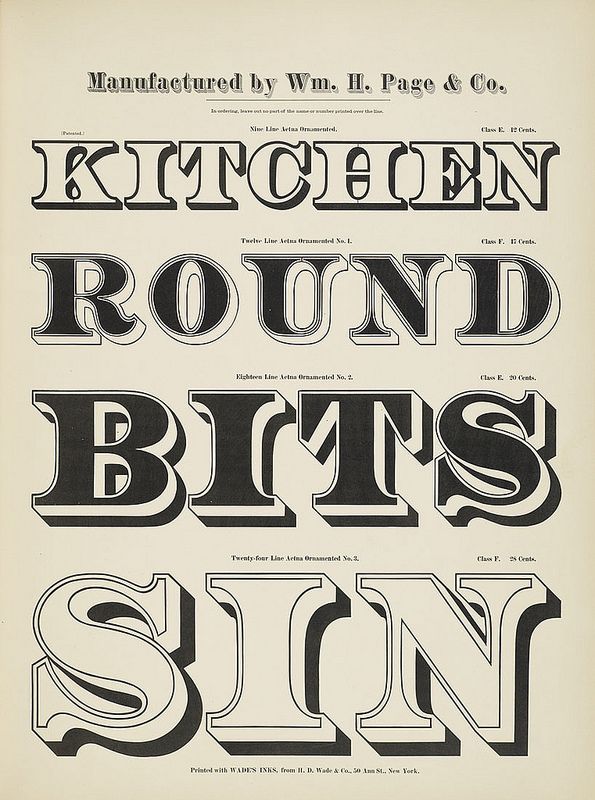
74. Шрифтовые формы XIX века
До
конца XVIII века различия между книжными,
рекламными и газетными шрифтами не
существовало, употреблялся один и тот
же шрифт, но разного размера. С активным
развитием промышленности и торговли в
XIX веке начали возникать новые стили
шрифтов для газетных объявлений, рекламы
и других акцидентных (т.е. выполняемых
по случайным, разовым заказам) работ.
Эти шрифты отличались от книжных особым,
бросающимся в глаза рисунком. Эксперименты
в области шрифтовой формы привели к
возникновению новых видов шрифта.
К
таким акцидентным
шрифтам принадлежит
появившийся в начале XIX в. египетский
или
брусковый
шрифт.
Отличительным
признаком этого шрифта является
одинаковая толщина всех линий и засечек
букв. При этом пропорции и расположение
засечек такие же, как у антиквы. Существуют
разновидности египетского шрифта с
большим или меньшим различием в
насыщенности основного и дополнительного
штриха. Известнейшие из типографских
египетских шрифтов — Мемфис и Бетон
работы немецких шрифтовиков Рудольфа
Вольфа и Гейнриха Иоста.
Существует
два подвида египетского шрифта.
Первый
из них — это итальянский
шрифт,
весьма популярный в XIX в. Это узкий шрифт,
по строению напоминающий рустику.
Горизонтальные штрихи в несколько
раз толще вертикальных.
Второй
подвид египетского шрифта — это
кларендон.
Его признак — слегка округленные засечки
и больший контраст между толщиной
основного и дополнительного штриха.
В
1816 году появляется шрифт, на фоне
многовекового господства антиквы
выглядевший странно и даже смешно,
за что и получил свое название — гротеск
(от
фр. смешной). Это шрифт с минимальным
контрастом между основным и дополнительным
штрихами и полным отсутствием засечек.
Гротески,
как и египетские шрифты, создавались в
качестве акцидентных и на большее не
претендовали. Однако в 1896 году берлинская
словолитня «Бертольд» выпустила
серию шрифтов, которые, несмотря на свое
название «Акцидент-гротеск», оказались
пригодными для набора текстов.
Акцидент-гротеску предстояло стать
прототипом новой шрифтовой эстетики.
Он появился незадолго до того, как
«новые типографы» назвали гротеск
«объективным и наднациональном шрифтом
современности». И действительно, именно
гротески обусловили облик типографики
XX в.
Кроме
названых шрифтов в XIX в. на фоне общего
упадка типографических традиций
появляется огромное количество
декоративных шрифтов, как правило —
искаженных, противоестественных форм.
Конструктивная неясность и декоративная
перегруженность таких шрифтов формировала
тенденцию к упадку художественного
шрифта во второй половине XIX в., периоде,
получившем название периода
типографической эклектики.
Примерно в 1808
году Пеллегрино
Турри (Pellegrino Turri), также известный как
изобретатель копировальной
бумаги, создаёт собственную печатную
машину. Подробности о его изобретении
сегодня неизвестны, однако до нашего
времени сохранились тексты, напечатанные
на этом устройстве.[3]
Эпоха
ренессанса не расширяла никогда
первоначальной формы шрифта. Дидо,
наоборот, выдвинул положение о серии
шрифтов — узких, широких, жирных, тонких
и т. д.
В
XIX в. было создано огромное количество
всевозможных шрифтов самых разнообразных
рисунков. В Англии в начале столетия
появляется характерная разновидность
шрифта с чрезвычайно тонкими дополнительными
штрихами и одновременно чрезвычайно
жирными основными.
Это
так называемый жирный гротеск Торна
(1803 г.), за которым последовал в 1824 г. еще
более жирный шрифт (рис. 318). Не следует
путать этот шрифт с гротесковыми шрифтами
в современном смысле этого слова. В
настоящее время мы называем гротесками
шрифты типа древнего (рубленый,
рояль-гротеск и т. д.).
Появление |
Застрельщиком
была Англия как страна с наиболее
развитой промышленностью. Континентальная
Европа покупала английские машины и
копировала английские шрифты. Франция,
Германия, Голландия, Испания выпустили
ряд шрифтов. Появились жирные шрифты
самых различных рисунков, соответствующих
рисункам светлых шрифтов.
Появление
гротесковых шрифтов (в современном
значении этого слова) относится к первой
половине XIX в.
Шрифты
в стиле модерн и экспериментальные
шрифты
своими характерными начертаниями ярко
отражали стиль того времени.
Лучшие
шрифты нашего времени созданы выдающимися
художниками шрифта.
Их благородные формы возникли в итоге
изучения красоты и практичности всех
прежних шрифтов. Создать шрифт могут
лишь немногие. Шрифтовое оформление
требует больших практических знаний.
Типографические шрифты часто
называют по имени создателей, но иногда
им дают звучные собственные имена.
В
XIX в. было создано огромное количество
всевозможных шрифтов самых разнообразных
рисунков. В Англии в начале столетия
появляется характерная разновидность
шрифта с чрезвычайно тонкими дополнительными
штрихами и одновременно чрезвычайно
жирными основными.
Появление
гротесковых шрифтов (в современном
значении этого слова) относится к первой
половине XIX в.
В
начале XIX в. появляется так называемый
«египетский» шрифте утолщенными
отсечками, перпендикулярными к основным
жирным штрихам.
Историческая
классификация наборного шрифта
Антиква |
|||
XV–XVI |
Гуманистическая (антиква |
Aa (Garamond) |
Шрифты |
XVII–XVIII |
Переходная антиква |
Aa (Caslon) |
Шрифты |
XVIII–XIX |
Классицистическая |
Aa (Bodoni) |
Шрифты |
Брусковые |
|||
Начало |
Египетские |
Aa (Luxor) |
Насыщенные |
Начало |
Итальянские |
Aa (Italiansky) |
Шрифты |
Начало |
Кларендон |
Aa (ScoolBook) |
Разновидность |
Гротески |
|||
Вторая |
Старые |
Aa (Gazeta) |
Ранняя |
20-е |
Геометрические |
Aa (Futura) |
Шрифты, |
50-е |
Новые |
Aa (Pragmatica) |
Моноширинные, |
50-е |
Гуманистические |
Aa (Optima) |
Шрифты |
Конец |
Динамические |
Aa (FreeSet) |
Разноширинные |
ренессансная антиква — Оди. О дизайне
27 Апр 2022
8771
0
Переходим к классификации текстовых шрифтов.
Паратайп
Паратайп — первая шрифтовая студия в России. Мы делаем новые шрифты, поддерживаем магазин paratype.ru, рассказываем о шрифте и типографике.
Если ориентироваться на форму, то в зависимости от степени контраста и наличия засечек они делятся на четыре основные группы: антиква, гротеск, брусковый шрифт и ленточная антиква/контрастный гротеск.
Антиква (Serif)
Из современных видов текстовых шрифтов первыми появились антиквы — шрифты с засечками и заметным контрастом между горизонтальными и вертикальными штрихами. До начала XIX века это был практически единственный тип шрифтов в Европе (если не считать готических шрифтов в Западной Европе и полууставных в Восточной).
Антиква старого стиля (Old style serif)
Отличается самой геометрически «неправильной» формой среди текстовых шрифтов. Это объясняется относительной близостью шрифтов этого типа к рукописному прототипу.
Как правило, для старостильной антиквы характерен умеренный контраст (1:2–1:3), открытость форм, наклонные оси овалов, часто — несимметричные засечки.
Антикву старого стиля можно назвать ещё динамической антиквой, т.к. формы, унаследованные от гуманистической каллиграфии, как бы помогают глазу двигаться по строке.
Старостильные антиквы с ярко выраженным характером больше всего подходят для набора текстов своего времени (от Ренессанса до барокко). Антиквы старого стиля с менее выраженным характером — самый подходящий шрифт для художественной литературы. Из-за небольшого контраста и открытости форм она легко читается в очень длинных текстах.
Антиквы старого стиля делятся на ренессансные (XV–XVI вв.) и барочные (XVII–начало XVIII в.). У каждой из этих групп по две подгруппы. Ренессансные антиквы бывают венецианские и итало-французские, а среди барочных антикв выделяют голландские и английские.
Венецианская антиква (Venetian old style serif)
Шрифт Николая Иенсона из книги Vitae Imperatorum, 1471 г.
Время появления: конец XV века
В двух словах: Самый ранний тип антиквы и самый близкий к каллиграфии ширококонечным пером. Несимметричные формы овалов и засечек, очень разноширинные пропорции, небольшой контраст, мелкие строчные буквы и длинные выносные элементы.
История и теория: Венецианская антиква — собирательное название ранних антиквенных шрифтов, в основном применявшихся венецианскими типографами конца XV века. Форма знаков основана на дуктальном принципе. Шрифты характеризуются умеренным контрастом, мощными короткими засечками, хорошо выраженным наклоном осей овалов. Пропорции знаков довольно широкие, знаки разноширинные. Круглые элементы имеют каллиграфические изломы, каплевидные элементы угловатые. Засечки чуть прогнутые. Соотношение величины строчных и прописных близко к золотому сечению. В оригинальных венецианских шрифтах этого периода не было курсивов, изобретенных позже. Характерная особенность – наклонная перекладина у строчной «е». Наиболее характерные шрифты этого типа – шрифты венецианского типографа и словолитчика Николая Йенсона (Nicholas Jenson, работал в 1470–80 гг.).
Примеры цифровых шрифтов
LazurskiLeksaLadogaVenetian 301
Итало-французская антиква (Garalde)
Фрагмент печатной книги 1597 г.
Время появления: конец XV века
В двух словах: Ранний тип антиквы, один из самых красивых в истории наборного шрифта. Встречается в лучших образцах ренессансной печатной книги. По форме мягче венецианской антиквы, детали более округлые. Несимметричные формы овалов, разноширинные пропорции, небольшой контраст, мелкие строчные буквы и длинные выносные элементы.
История и теория: Гаральды или итало-французская антиква старого стиля — собирательное название группы ранних антиквенных шрифтов, основанных на шрифтах венецианского типографа и издателя Альда Мануция (Aldus Manutius, 1447–1515) работы болонского гравера Франческо Гриффо (Francesco Griffo, ок. 1450–1518) и парижского словолитчика Клода Гарамона (Claude Garamond или Garamont, ок. 1490–1561). Название «Гаральды» означает шрифты, близкие к ГАРамону и АЛЬДу.
Aldus ManutiusClaude Garamond
Развитие венецианской антиквы в конце XV–XVI в.в. Название придумано французским исследователем типографики Максимилианом Воксом (Maximilien Vox) в 1954 г. Форма знаков похожа на структуру предшественников и еще основана на дуктальном принципе, но заметно меняется под воздействием типографской практики и теорий построения шрифта Луки Пачоли (Luca Paccioli, ок. 1445–1514) и Жоффруа Тори (Geoffroy Tory, 1480–1533). Шрифты характеризуются небольшим контрастом, пропорциями золотого сечения, разноширинностью знаков, плавным присоединением засечек, наклонными осями овалов. Засечки становятся более длинными и острыми, верхние выносные элементы обычно заметно выше прописных. Впервые у Альда применяется строчной курсив с небольшим наклоном как альтернативный текстовой шрифт, но затем курсив рассматривается как дополнительное начертание к прямому, он согласовывается по размеру, цвету и форме, в нем появляются наклонные прописные. В курсиве наклон у прописных меньше, чем у строчных. Строчные курсивные знаки имеют разный наклон.
Примеры цифровых шрифтов
Aldine 401Iowan OldstyleRevival 565
Зачем в 2020-х годах может понадобиться ренессансная антиква?
Хотя этому типу шрифтов пятьсот с лишним лет, он прекрасно работает в тексте. Правда, не в любом: в качестве основного шрифта, например, на новостном сайте ренессансная антиква будет выглядеть странно. А вот в издании (в том числе электронном) на историческую тему в качестве заголовочного шрифта, в красивой книге с большими полями (особенно в волшебных сказках) для основного текста, или для создания нужной атмосферы — вполне! Особенно сильное впечатление производит ренессансная антиква, если набрать пару слов прописными с очень сильной разрядкой.
В следующей части мы расскажем о барочной антикве.
Первая часть.
Шрифты 1800-х годов: 35 лучших шрифтов 19-го века
Для графического дизайнера шрифты являются неотъемлемой частью вашего набора инструментов. Они делают или разрушают ваши проекты.
Шрифты 1800-х годов особенно привлекательны. Эпоха пережила революцию в шрифтах и типографике, и ее влияние все еще присутствует в современном графическом дизайне. Многие шрифты 19-го века причудливы и уникальны, с большим характером. Если вы хотите придать своему дизайну ощущение старины, это идеальный выбор.
Здесь вы найдете коллекцию лучших современных шрифтов, которые были разработаны, чтобы воспроизвести стиль 19-го века. От сложных рукописных шрифтов до классических шрифтов с засечками — здесь каждый найдет что-то для себя.
НЕОГРАНИЧЕННАЯ ЗАГРУЗКА: более 50 миллионов дополнений и ресурсов дизайна
Лучшие шрифты 1800-х годов Шрифты 19 века! Они выведут ваш винтажный дизайн на новый уровень.
Если вы любите шрифты, вам определенно стоит попробовать Envato Elements. Подписавшись на Elements, вы получите 90 009 неограниченных загрузок более 45 000 шрифтов , а также миллионов других ресурсов , таких как темы WordPress, стоковые фотографии, графика, звуковые эффекты и многое другое. Это лучшая ценность, которую вы можете найти в индустрии дизайна.
Euphoria
Euphoria — отличное семейство шрифтов 1800-х годов. Всего имеется 11 шрифтов, в том числе:
- Euphoria Victorian
- Euphoria Victorian Shadow
- Euphoria Victorian Gradient
- Euphoria Tuscan
- Euphoria Tuscan Gradient
- Euphoria Tuscan Outline
- Euphoria Serif
- Euphoria
- Euphoria Expand Bold
- Euphoria Sans
03 Serif10 Shadow
In Кроме того, пакет также поставляется с некоторыми дополнительными глифами для стилизации вашего текста. Чтобы использовать глифы, вам понадобится программа (например, Photoshop или Illustrator), поддерживающая функции OpenType.
Euphoria действительно больше, чем просто шрифт. Это набор красивых винтажных шрифтов, которые дают вам множество вариантов, когда вы хотите почувствовать аутентичность 1800-х годов.
Bahud Aroyek Декоративный шрифт 1800-х годов
Bahud Aroyek — это шрифт для дисплеев, созданный с искусным викторианским шрифтом. Он элегантный и идеально подходит для широкого спектра проектов, таких как брендинг, упаковка продуктов, одежда, товары и печатные материалы, такие как приглашения. Вам понравятся альтернативные стили и лигатуры, которые позволяют создавать текст, который выглядит так, как будто он был создан на заказ. Версия веб-шрифта также включена.
Chesterfield
Chesterfield — потрясающий шрифт 19 века, вдохновленный карнавальными, цирковыми и татуировками 1800-х годов. Благодаря декоративному стилю Chesterfield лучше всего смотрится в крупном тексте. Включены три варианта: обычный, обычный градиент и экструдированный. Пакет также включает 30 винтажных векторных форм, которые идеально подходят для создания значков и вывесок.
White Castle
White Castle — это викторианский шрифт, который прекрасно подходит для винтажных дизайнов. Это шрифт с заглавными буквами, в котором строчные буквы являются альтернативными версиями стилей в верхнем регистре. Также доступна версия веб-шрифта. Вам понравится использовать White Castle для брендинга, вывесок, значков и других винтажных дизайнов.
Taberna
Taberna — это огромная система шрифтов, включающая более 20 шрифтов 1800-х годов. Вы получите разновидности с засечками и без засечек с многоуровневыми версиями, которые можно накладывать друг на друга, а также монолинерный рукописный шрифт 19-го века. С Taberna в вашем арсенале у вас всегда будет доступ к множеству вариантов. Вам понравится использовать его для плакатов, заголовков, рекламы, этикеток продуктов, одежды и многого другого.
Liquidior
Liquidior — чистый шрифт с винтажным шармом. Он был вдохновлен древнегреческой типографикой, и вы обязательно найдете множество способов использовать его в своей работе. В пакет входят цифры, знаки препинания, лигатуры, многоязычные символы, а также некоторые значки и иллюстрации, которые можно использовать с текстом.
Wakers Amor
Wakers Amor — это шрифт blackletter с характером и стилем 1800-х годов. Он был создан с использованием викторианской типографики ручной работы и является отличным выбором для вывесок, брендинга, плакатов и других дизайнов с крупным текстом. Вы получите лигатуры, стилистические варианты, многоязычные символы и веб-шрифт.
Reborn
Reborn — многоуровневая система, включающая четыре шрифта: базовый, встроенный, теневой и орнаментальный. Вы можете использовать любой из шрифтов по отдельности или сложить их так, как вам хочется. Он поставляется с цифрами, пунктуацией и многоязычными символами. Вам понравится использовать Reborn для плакатов, листовок, упаковки продуктов, этикеток продуктов, брендинга, футболок, товаров и многого другого.
Гнилой банкет
Гнилой банкет может показаться странным названием, но оно станет выдающимся дополнением к вашей коллекции. Дизайнер был вдохновлен викторианской типографикой 19 века. Это декоративно, но все же легко читается. Пакет поставляется с огромной коллекцией из 370+ глифов для использования вместе с вашим текстом.
The Bhorthead
The Bhorthead — красивый винтажный шрифт для штампов, который идеально подходит для этикеток продуктов, упаковки продуктов, футболок, одежды, товаров и брендинга. Есть две версии: чистая и шероховатая (текстурированная), что обеспечивает дополнительную универсальность. Вам также понравится коллекция стилистических альтернатив, лигатур и размытий.
Гарнитура Vanberg 19th Century
Vanberg — это декоративный акцидентный шрифт с большим шармом 19-го века. Это винтажный шрифт, состоящий только из заглавных букв, а строчные буквы являются стилистическими альтернативами. Vanberg лучше всего работает с крупным текстом, поэтому он идеально подходит для заголовков, плакатов, обложек альбомов, футболок и т. д. Это смелый шрифт, который идеально подходит, когда вы ищете винтажную типографику с ощущением Дикого Запада. Пакет поставляется с четырьмя различными стилями: обычный, гранж, шпора и тень. Используйте их вместе или по отдельности, чтобы получить желаемый результат. Lawless лучше всего подходит для крупного текста, когда вы хотите сделать смелое заявление.
Pollyester
Pollyester — это шрифт blackletter, сочетающий в себе современную и классическую типографику. В отличие от некоторых других староанглийских шрифтов или шрифтов blackletter, Pollyester ясен и легко читается. Он поставляется со стилистическими альтернативами и лигатурами, которые упрощают создание индивидуального образа. Веб-шрифт также включен.
Sicero
Sicero — это дуэт, который включает шрифты без засечек и римские (с засечками). Оба отлично подходят для использования в вывесках, брендинге, рекламе, изображениях в социальных сетях, заголовках и многом другом. Также доступна версия веб-шрифта.
Hidrofont
Hidrofont — богато украшенный винтажный шрифт, сочетающий типографику 19 века с современными характеристиками. Как элегантный современный шрифт, он отлично подходит для брендинга, приглашений, вывесок, упаковки, этикеток, одежды и многого другого. Загрузка включает в себя бонусные росчерки и веб-шрифт.
Chief Cart Шрифт 1800s
Chief Cart украшен викторианскими надписями ручной работы. В каждую букву вложено много труда. Лучше всего использовать крупный текст, чтобы детали в буквах были легко видны. В пакет также входят альтернативы и лигатуры.
Humoresque
Humoresque — это огромное семейство из 12 многослойных шрифтов, которые можно смешивать и сочетать для создания бесконечного разнообразия образов. Он был вдохновлен декоративным шрифтом рубежа веков и, несомненно, станет забавным дополнением к вашему набору инструментов. Используйте его для вывесок, брендинга, плакатов и т. д.
Forbes
Этот богато украшенный и декоративный шрифт в стиле ретро — отличный выбор для разработки этикеток, упаковки, брендинга, рекламы, одежды и многого другого. Написанный викторианским почерком, он обязательно произведет впечатление. Загрузка включает две разные альтернативные версии, лигатуры, многоязычную поддержку и веб-шрифт.
Aspernatur
Aspernatur — это винтажный акцидентный шрифт, вдохновленный буквами конца 1800-х годов. Орнаментальный шрифт может найти место в ваших дизайнерах для плакатов, обложек книг и других винтажных проектов. В пакет входит веб-шрифт.
Historica Typeface
Это многоуровневое семейство шрифтов включает пять вариантов, которые можно накладывать друг на друга или использовать по отдельности. Это идеальный выбор для вывесок, плакатов, товаров, одежды и многого другого. Пакет включает в себя цифры, знаки препинания и некоторые бонусные винтажные векторные уголки.
Elkarnito
Этот дизайнер Elkarnito был вдохновлен винтажными буквами, и в результате получился удивительный шрифт с широким спектром применения. Вы получите прописные буквы, строчные буквы, цифры, знаки препинания, лигатуры и многоязычные символы. Вам понравятся бонусная графика и лозунги, включенные в файлы PNG, идеально подходящие для использования с вашим текстом. Версия веб-шрифта также включена.
Rusty Store
Rusty Store — элегантный шрифт с засечками, очень декоративный в старинном стиле. Это не самый простой для чтения, но идеальный вариант, если вам нужен шрифт 1800-х годов, обладающий удивительной винтажной привлекательностью. Пакет поставляется с альтернативами, глифами и веб-шрифтом.
Maron King
Maron King — это шрифт для дисплеев, вдохновленный как викторианским, так и классическим стилями. Это универсальная коллекция, которая включает в себя прописные и строчные буквы, множество альтернатив, цифр, знаков препинания, акцентов, лигатур и веб-шрифта. С включением альтернатив вы можете смешивать и сочетать, чтобы создать текст, который выглядит так, как будто он был разработан специально для вас.
Gibswing
Gibswing — впечатляющий пакет, включающий три различных шрифта (с засечками, обычный и заглавные), а также некоторые декоративные элементы. Причудливая надпись хорошо подходит для вывесок, значков, баннеров, брендинга и многого другого. Gibswing Regular включает прописные и строчные буквы и, вероятно, будет тем, который вы используете чаще всего, а остальные являются декоративными вариантами. Включена поддержка многих языков.
Angwie
Angwie — это шрифт с засечками, выполненный с использованием викторианского рукописного письма. Он состоит из заглавных букв и использует строчные буквы, чтобы обеспечить альтернативу прописному стилю. Вы также получите лигатуры, цифры и знаки препинания. Angwi лучше всего работает с большими размерами текста.
Stay Alive
Stay Alive — один из лучших шрифтов 19 века в красивом викторианском стиле. Он поставляется с цифрами, пунктуацией, многоязычными символами, лигатурами и стилистическими альтернативами. Stay Alive — отличный вариант для брендинга, плакатов, этикеток продуктов, упаковки, футболок и товаров.
Ehrich
Ehrich — великолепный шрифт, представленный в обычных и грубых вариациях. Он пишется заглавными буквами, поэтому он не будет подходящим выбором для каждого проекта, но Ehrich определенно найдет место в вашей работе. Вдохновленный старинной волшебной рекламой, Ehrich идеально подходит для заголовков, плакатов, листовок, рекламы и многого другого.
Winchester
Winchester — декоративный шрифт blackletter, созданный вручную. Загрузка включает в себя множество альтернатив, лигатур и многоязычных символов, а также версию веб-шрифта.
Boston 1851
Boston 1851 отличается от других представленных здесь. Этот шрифт хорошо работает с мелким текстом и повторяет внешний вид печати и шрифтового дизайна 1800-х годов. Вдохновленный стереотипом, установленным и используемым в Бостоне, он имеет очень аутентичный внешний вид. Пакет включает в себя несколько вариантов, а также коллекцию из более чем 600 глифов.
Korenah Serif
Korenah Serif — красивый шрифт в винтажном стиле. Пакеты поставляются с прописными и строчными буквами, цифрами, пунктуацией, многоязычными символами, лигатурами, альтернативами и веб-шрифтом. Это очень универсальный шрифт, который можно использовать во многих проектах.
Бесплатные шрифты 1800-х годов
Выше мы продемонстрировали лучшие шрифты 1800-х годов, но вы, возможно, ищете бесплатную альтернативу. Есть несколько бесплатных шрифтов 19-го века, но выбор гораздо более ограничен. Когда вы используете бесплатные программы, обязательно ознакомьтесь с условиями лицензии, поскольку коммерческое использование может быть запрещено.
Hustlers Rough
Демо-версия Hustlers Rough — это бесплатный шрифт для личного использования. В нем нет цифр и знаков препинания, но буквы красиво оформлены.
Sancreek
Sancreek бесплатен для личного или коммерческого использования. Включены прописные и строчные буквы.
Traditio AH
Traditio AH бесплатен только для личного использования. Надпись основана на рекламе немецкого пива.
Walbaum Fraktur
Walbaum Fraktur выпускается в четырех исполнениях и может использоваться в коммерческих проектах.
DS Fette Kanzlei
DS Fette Kanzlei можно использовать для коммерческих проектов. Он украшен витиеватыми декоративными буквами.
Заключительные мысли о шрифтах 1800-х годов
Если вы создаете винтажный дизайн и хотите, чтобы внешний вид или стиль 19-го века, самый простой способ сделать это — использовать один из лучших шрифтов 1800-х годов, представленных здесь. Эти шрифты были созданы с особой тщательностью, чтобы имитировать типографику 19 века.
Лучшие шрифты XIX века с неповторимым характером и шармом станут отличным дополнением к вашему арсеналу.
Шрифты викторианской эпохи: лучшие шрифты викторианской эпохи XIX века
Викторианская эпоха в Англии длилась от коронации королевы Виктории в 1837 году до ее смерти в 1901 году. Этот исторический период тесно связан с технологическими преимуществами британской промышленной революции. Он представил тысячи невиданных ранее изобретений и технологий. Многие из них произвели революцию в представлениях людей о производстве, маркетинге и даже графическом дизайне.
Более причудливые, чем гладкие и простые шрифты в стиле ар-деко, но менее адреналиновые, чем шрифты Дикого Запада того же века, викторианские шрифты узнаваемы по своему орнаменту и богатому замысловатому декору. По мере того, как конкуренция продуктов в постиндустриальной Англии резко возрастала, рос и спрос общественности на смелую, яркую и привлекательную типографику.
Использование декадентских цветовых наслоений, бордюров, декоративной отделки и плавных букв стало доминирующим стилем того времени. Эти обогащающие шрифты до сих пор вызывают волнение того времени, когда предметы роскоши наконец стали доступны незнатным людям. И привнести сентиментальную ностальгию в любой творческий проект.
Лучший выбор для викторианских шрифтов
Шрифт Top 1800s
Одним из самых популярных и коммерчески успешных шрифтов 19-го века был шрифт Fat Face. Это семейство шрифтов было разработано путем слияния двух традиционных шрифтов Dido и Bodoni. Но сделал их темнее, смелее и визуально более внушительными.
Шрифт
Mammoth Fat Face отдает дань уважения тем оригинальным наборщикам, которые (в буквальном смысле) сломали шаблон, чтобы дать миру самый популярный шрифт 19-го века.й век.
Лучшая викторианская типография
По мере того, как все больше и больше продуктов заполняло страницы, дизайнеры продуктов проявляли все большую изобретательность при разработке плакатов, логотипов и этикеток для продуктов.
Викторианские вывески и типографика, такие как Old Aflie, следовали изяществу и деликатности предыдущих стилей шрифта. Но стал более смелым, ярким и декоративным, чтобы выделиться из толпы.
Верхняя часть Викторианской надписи
Хотя преобладающим стилем той эпохи был автоматизированный и орнаментальный стиль, по-прежнему ценилась ручная работа, отнимающая много времени.
Helsing может резко контрастировать с большими, жирными и яркими шрифтами постиндустриальной викторианской эпохи. Но он улавливает сопоставление красоты простоты с технологиями.
Обзор лучших шрифтов викторианской эпохи
Некоторые изобретения, такие как печатные СМИ, графический дизайн и даже современные рекламные технологии, были разработаны в это время быстрых экономических изменений. Новые продукты начали заполнять страницы английских газет. В конце концов были введены «каталоги товаров» (предки наших журналов), чтобы помочь викторианцам выбирать, что они могут купить.
Печатная реклама в газетах и журналах была введена для новых брендов, чтобы зарекомендовать себя среди потребителей, а также конкурировать друг с другом. Технологии цветной печати также отрабатывались и производились серийно.
В результате викторианская типографика стала более смелой, красочной и стилизованной. Это, в дополнение к многослойным, текстурированным и заключенным в оболочку визуальным элементам, стало нормой того периода.
1. Толстая морда мамонта
● Шрифт высокой печати Fat Face
● $
● Прописные и строчные глифы, цифры и 32 символа
Набор
Mammoth Fat Face вдохновлен нарушителями правил викторианской эпохи, которые пошли против традиций. Они объединили классические стили Bodoni и Dido, чтобы создать шрифт, известный нам как Fat Face.
В отличие от эдвардианцев, которые упивались традициями и эстетической сдержанностью, викторианцы обожали заново изобретаемые шрифты. В частности, те, которые отказались от более традиционных подходов к графическому дизайну.
Несмотря на свою невероятную популярность в 1800-х годах, этот стиль шрифта по-прежнему является нестареющей классикой, которая подходит как для классических, так и для современных проектов.
Нажмите, чтобы проверить цену
2. Старый Алфи
● Украшенный винтажный дуэт шрифтов
●
$ ● Два шрифта, сорок векторных орнаментов и двадцать нарисованных от руки викторианских цветочных орнаментов.
Викторианская эпоха была временем новых изобретений, продуктов и процессов. Одним из таких изобретений, изменивших мир, была цветная литография. Это творение позволило дизайнерам воспроизвести сотни визуальных печатных копий с минимальными усилиями.
Хотя эта технология в основном использовалась художниками и иллюстраторами, способность быстро воспроизводить изображения в цвете была с готовностью включена в новооткрытый мир викторианского товарного маркетинга.
Вдохновленный этой технологической инновацией, Old Alfie использует те же смелые и многослойные цвета, которые отличают викторианцев визуально от любого предыдущего десятилетия.
Нажмите, чтобы проверить цену
3. Хельсинг
● Шрифт с засечками
● $$
● Включает прописные и строчные буквы, а также знаки препинания
Helsing отходит от более коммерческих воспоминаний о викторианской эпохе и подчеркивает простой стиль ручной работы века. Этот шрифт отлично подходит для тех, кто ищет тонкий викторианский шрифт. В частности, тот, который намекает на класс викторианской Англии без подавляющего орнамента, цветов и визуальных слоев.
Он хорошо служит в качестве более крупного визуального элемента, но ему не хватает того же привлекательного чутья, что и другим викторианским шрифтам. По этой причине он может быть более эффективным в качестве основного текстового приложения или для проекта с большим объемом текста, чем плакат или этикетка.
Нажмите, чтобы проверить цену
4. Арлингтон
● Многослойные винтажные надписи
● $$
● Прописные и строчные буквы, знаки препинания, символы, цифры и четыре варианта оформления
До индустриализации чрезмерная отделка и украшения были способом для благородных классов выставить напоказ свое богатство и классовый статус. Этот шрифт идеально подходит для логотипов и постеров. Он богато украшен, но привлекает внимание. Он был создан специально для того, чтобы помочь вам поднять ваш дизайн до уровня Victorian Royals 9.0003
Арлингтон черпает вдохновение в золотом веке шоппинга, когда новая демографическая группа Британии внезапно получила доступ как к базовым, так и к предметам роскоши по конкурентоспособным ценам, которые мог себе позволить каждый.
Нажмите, чтобы проверить цену
5.
Королевская вывеска
● Декоративный винтажный шрифт
● $$
● Набор символов A-Z, включая прописные и строчные буквы
Когда массовое производство стало способно воспроизводить ручную работу, замысловатый орнамент стал эстетической характеристикой многих продуктов, витрин и логотипов продуктов. Это использовалось как средство намека на дворянство и класс. Этот шрифт включает в себя символы с диакритическими знаками, стилистические варианты, цифры, знаки препинания и 40 векторных орнаментов и рамок.
Если вы сами ищете впечатляющий шрифт для продвижения своего бренда, Royal Signage — это красиво украшенный викторианский шрифт. Кроме того, в нем достаточно декоративных элементов, чтобы упасть в обморок любому викторианцу.
Нажмите, чтобы проверить цену
6. Викториандеко
● Декоративный шрифт в античном стиле
● $
● Включает прописные и строчные буквы, знаки препинания и бонусную векторную рамку
Victoriandeco — старинный шрифт, посвященный викторианскому периоду истории. Буквы жирные, но витиеватые. И с гравийной текстурой, чтобы придать ему общий вид, похожий на винтажную безделушку на блошином рынке — редкую, подлинную и часть истории.
Следуя эстетическому характеру плавных и декоративных надписей и акцентов, этот шрифт 19-го века хорошо подходит для плакатов, логотипов и общего графического дизайна.
Нажмите, чтобы проверить цену
7. Выпуклости
● Многослойная викторианская вывеска
●
$ ● Три взаимозаменяемых типа слоев и дополнительный орнамент.
Еще один викторианский шрифт для надписей, который идеально подходит для графического дизайна, Bulges — это многослойный викторианский шрифт для вывесок. Он включает в себя элегантные элементы современного дизайна и сочетает их с классическими 19чутье века.
Он включает вставку и тень, которые вы можете легко применить или удалить в зависимости от потребностей вашего проекта. Подобно этикеткам продуктов, которые в значительной степени зависели от визуальных элементов логотипа, этот шрифт содержит слои сценариев. Это позволяет легко воспроизводить сложные и богато украшенные детали викторианских изображений.
Нажмите, чтобы проверить цену
Почему выбирают типографику викторианской эпохи?
Викторианская эпоха и промышленная революция изменили отношение Британии и остального мира к промышленным товарам. Легко принять как должное технологии, пришедшие из этой эпохи, но трудно забыть, как этот внезапный всплеск потребительства все еще влияет на наш мир сегодня.
Графические стили викторианской эпохи могут быть устаревшими, но они легко узнаваемы. Они связаны с захватывающими изменениями, новыми технологиями, меняющимися временами и доступной роскошью.